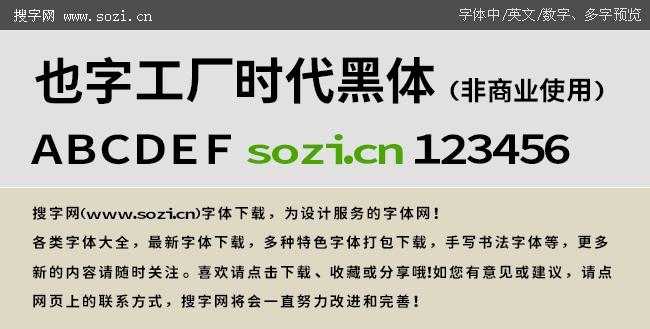
也字工廠時代黑體
搜字網(wǎng)給大家提供一款也字工廠時代黑體(非商業(yè)使用)中文字體下載,也字工廠時代黑體是一款黑體字體,字體簡潔有力,醒目大方,具有很好的視覺效果。適合應用于海報設計、包裝設計、網(wǎng)頁設計等應用(此字體為個人非商用版,商用可以聯(lián)系:官方網(wǎng)址:https://yefont.com/home,聯(lián)系方式:13798980448)。